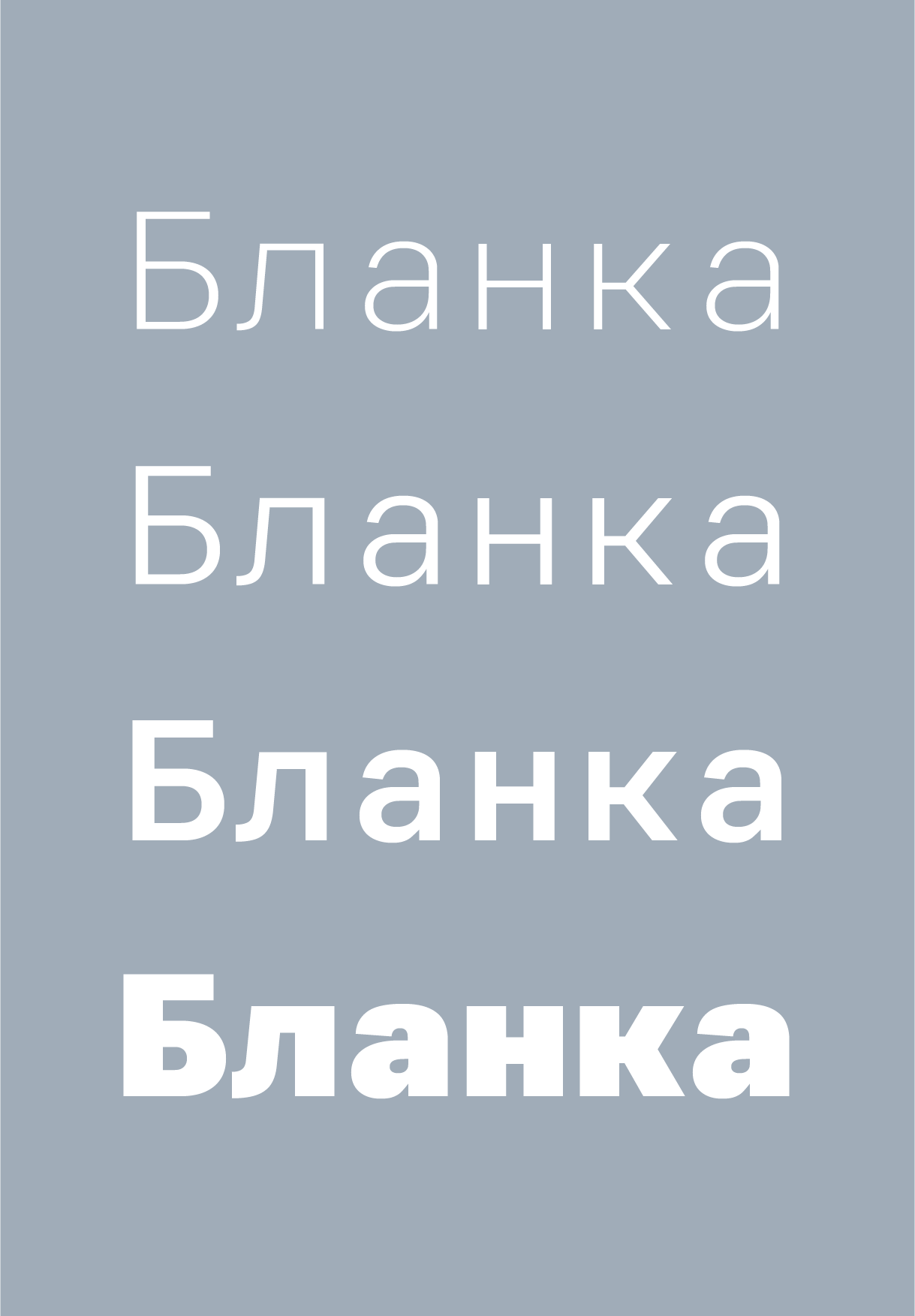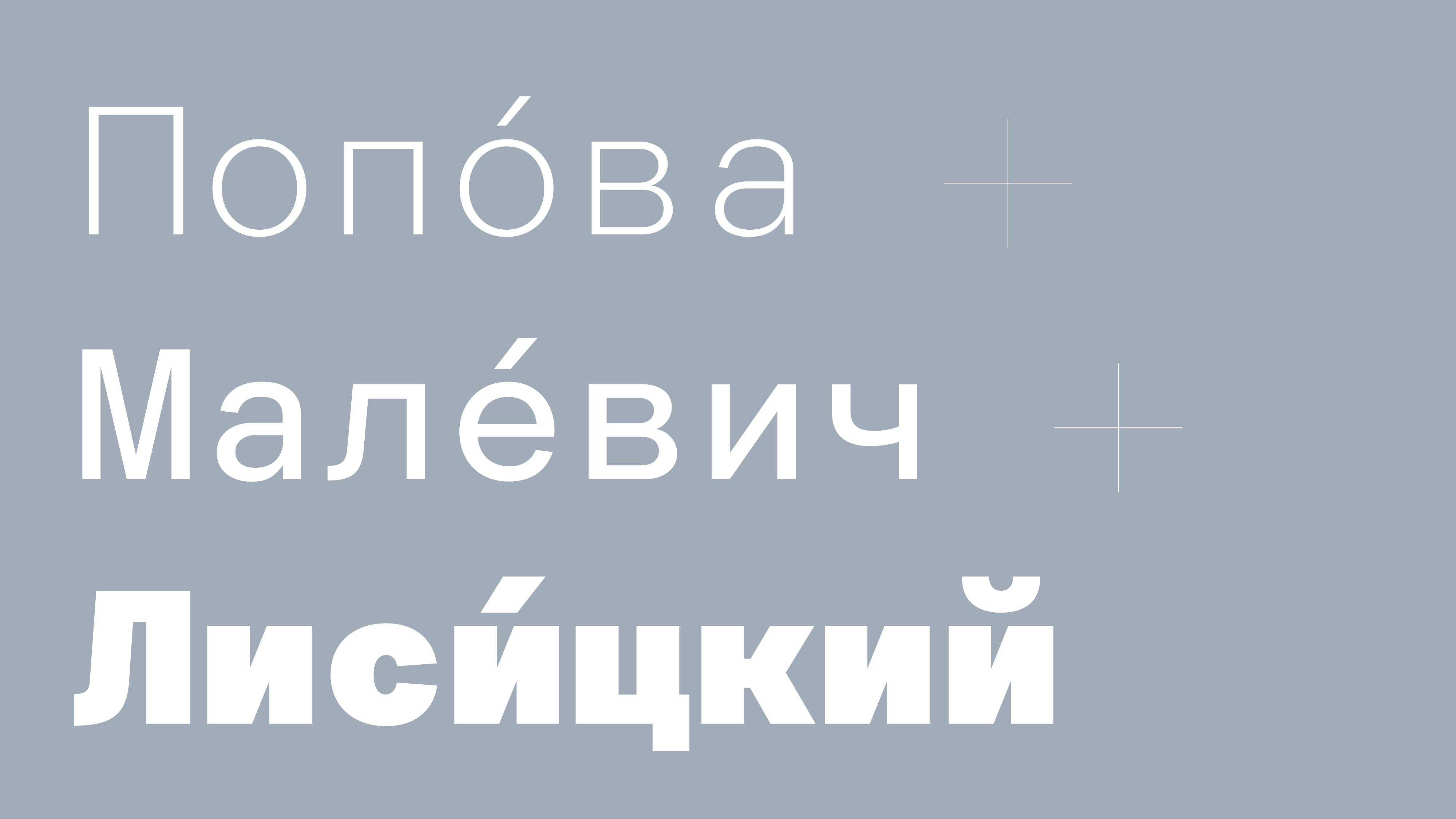
F37 Blanka Mono Cyrillic Font Sampler
Blanka — чистый классический швейцарский шрифт от F37. Идеально подходит для основного текста, он экономичен, функционален и легко читается при небольших размерах.